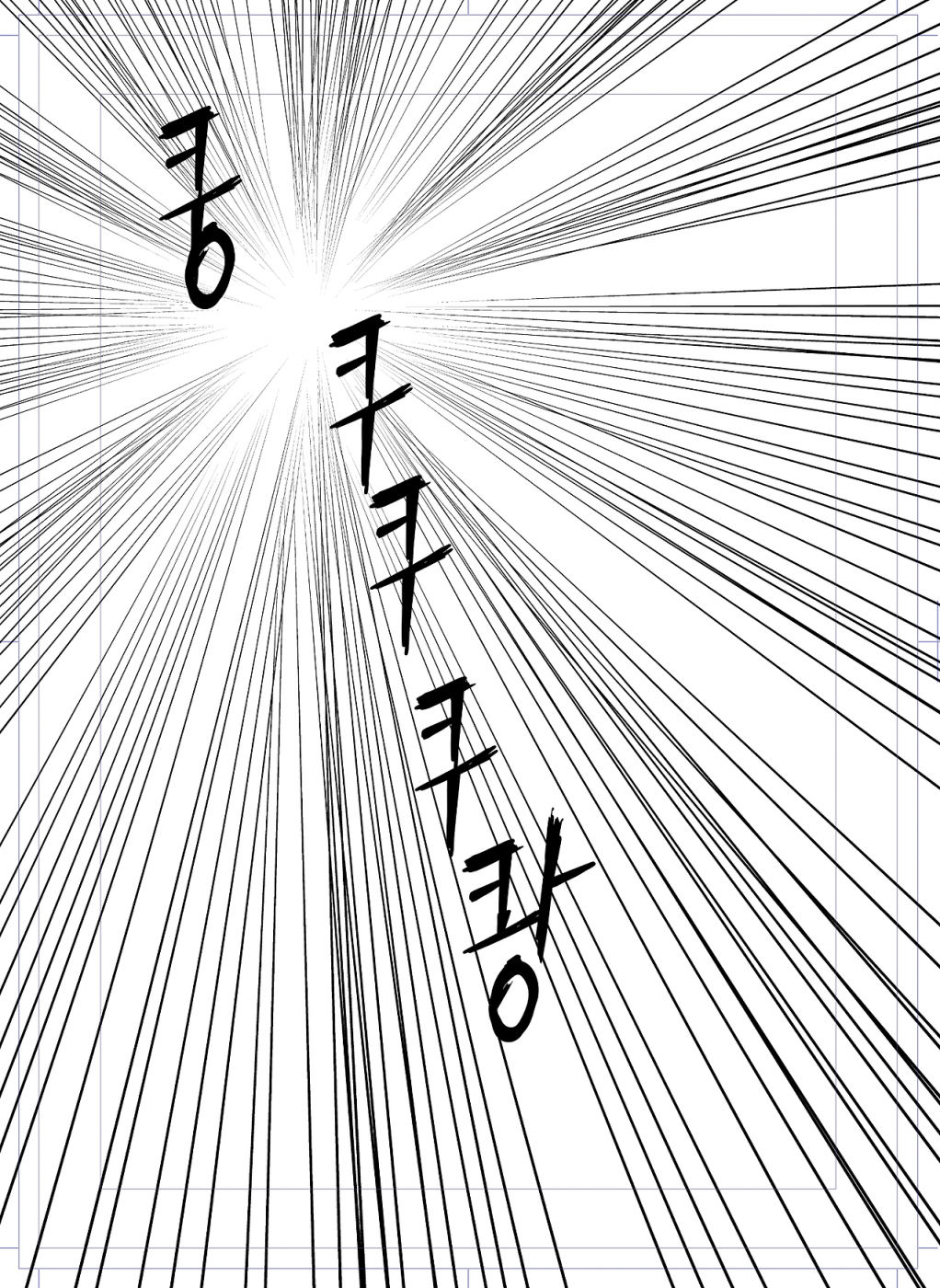
클립스튜디오 한글 효과음 폰트에디터
Clip Studio만화 폰트가 아닌 폰트편집기로
Clip Studio 는 만화가, 웹툰작가가 포토샵만큼 많이 쓰는 도구입니다. 초기버전부터 지금까지 전부 써온 프로그램인데 일본에서 만들어서 그런지 한글효과음에 대한 부분이 미흡 아니 벡터부분에 대한 기능이 많이 떨어집니다.
개발이 대부분 3D나 작화에 도움이 되는 기능들 우선순위 인 것이고 효과음이나 말풍선은 대부분 작가가 어느정도 참여해야하는 것으로 생각해서 그런지 몰라도 기능이 아직 요원합니다. 그래서 폰트가 나온 거 같기도 한데 개인적으로 작가의 작품에 어울리는 효과음은 작가가 만들어서 만화의 개성과 연결하는 일관성이 있어야 한다고 생각합니다.
그래서 초기부터 폰트 만들 때 만화효과음 전문 편집이 가능한 별도의 프로그램을 생각했고 제가 쓴 악당의 명언도 약간 만화 효과 느낌의 원고지 같은 내지를 사용했습니다.
한참 고민하다가 이번에 여러 프로그램 업그레이드도 하고 앞으로 캔바나 영상관련 자막에 사용할 초성, 중성, 종성의 키네틱 애니메이션을 포함하고자 여러 툴과 경쟁력이 있는 것을 만들 준비를 했습니다.
만화효과음 폰트나 몇 종 더 만들고 이제 효과음 한글폰트 편집기는 마무리단계로~ 다국어 폰트도 그 자리에~ 배치하는 것으로 일단 만화전용 간단한 폰트편집기 같은 개념을 가진 프로그램으로 개발하고 있습니다. 클립스튜디오에 바로 가져올 수 있게 배치합니다.
만화 효과음은 더 화려하게도 할 수 있지만 일단 여기까지 샘플로 작업했습니다.  자소음만 넣으면 고유의 만화용 한글 효과음 작업이 됩니다. 웹툰 기술지원사업 관련된거나 해보는게 어떨까 합니다.